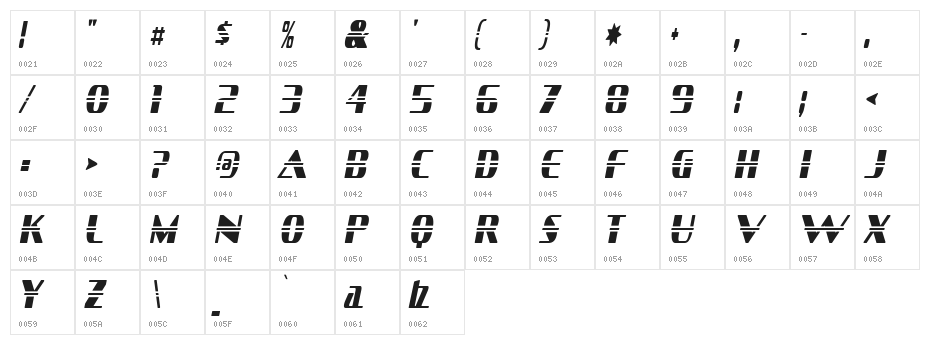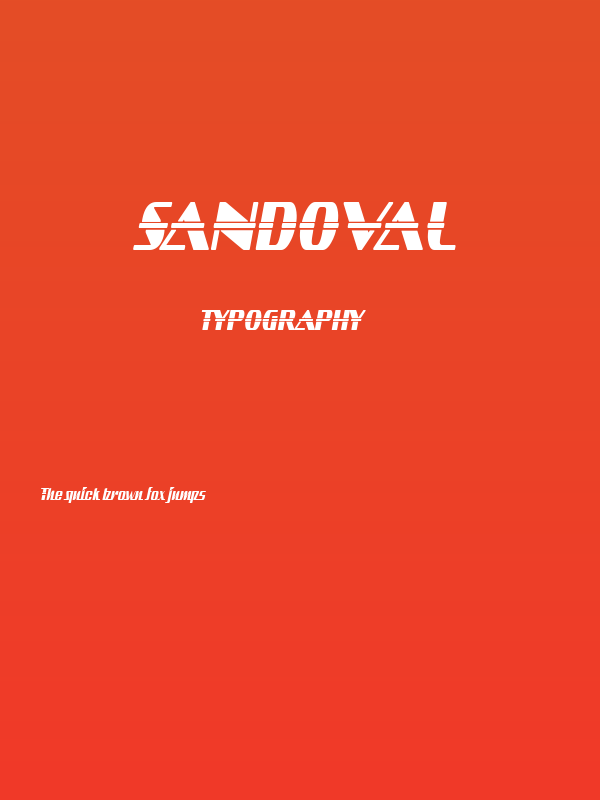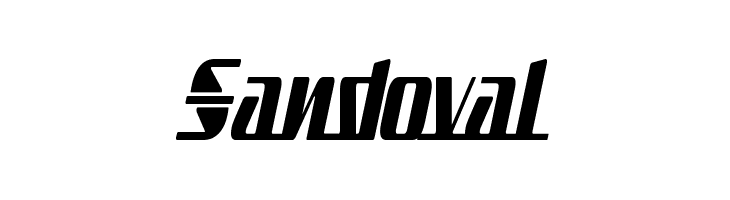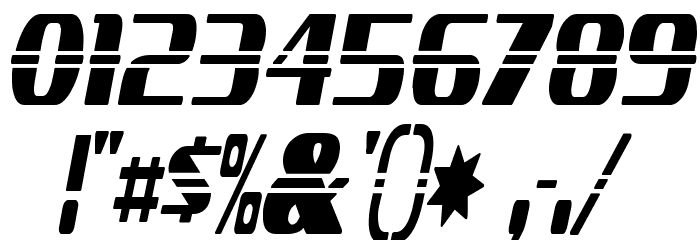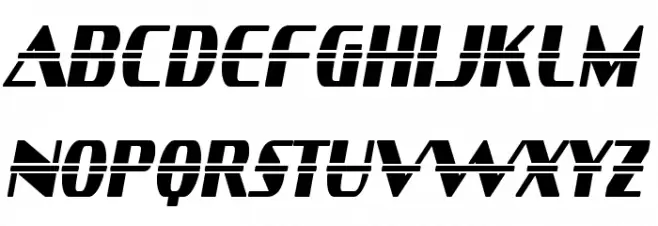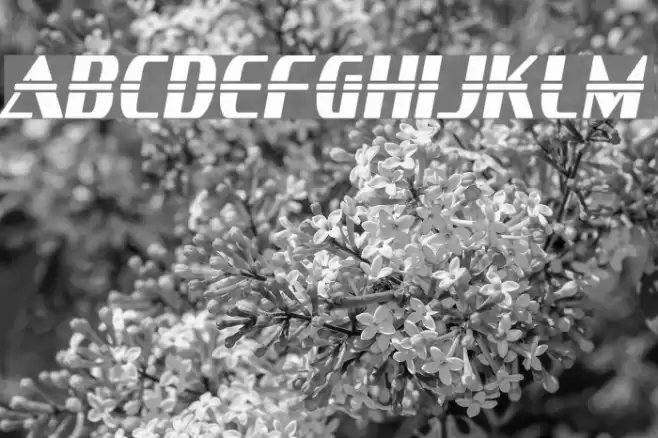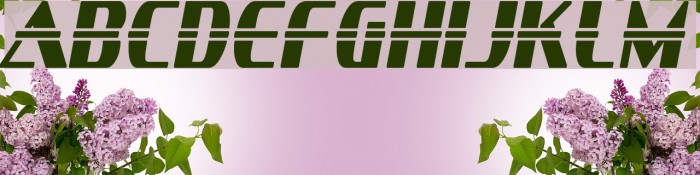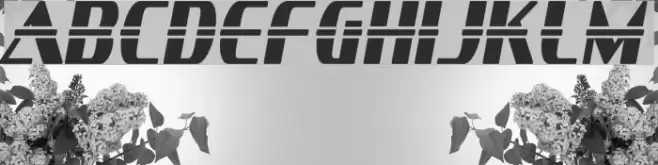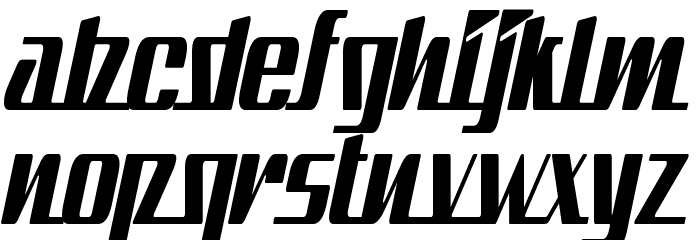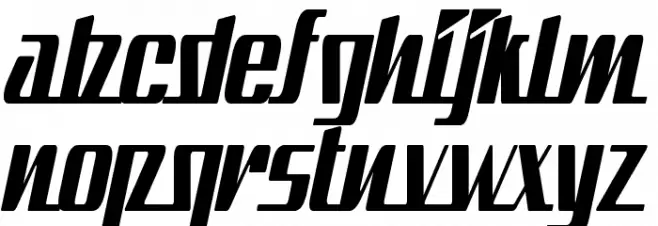
Sandoval Font
| Caso d'uso | Logos, Headlines, Branding |
| Progetti proposti | Ideal for sports branding, automotive designs, tech-related projects, and modern advertising. |